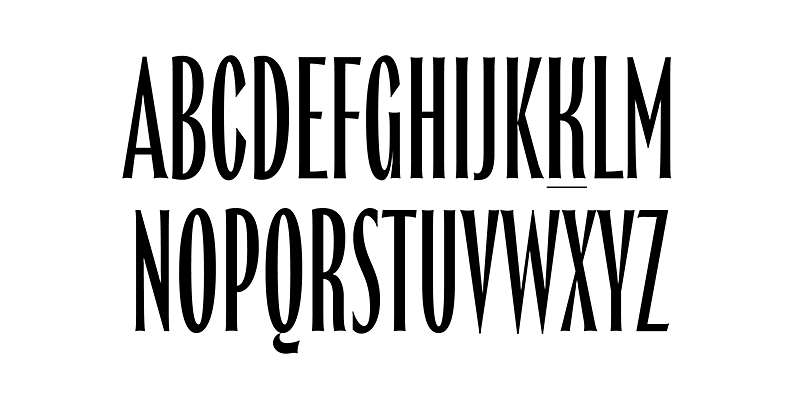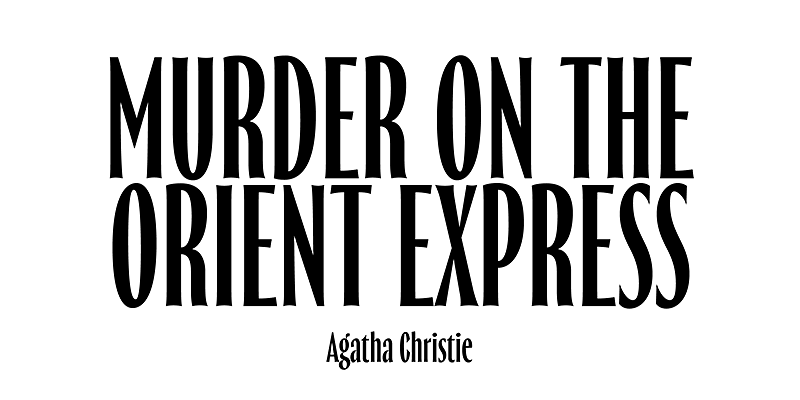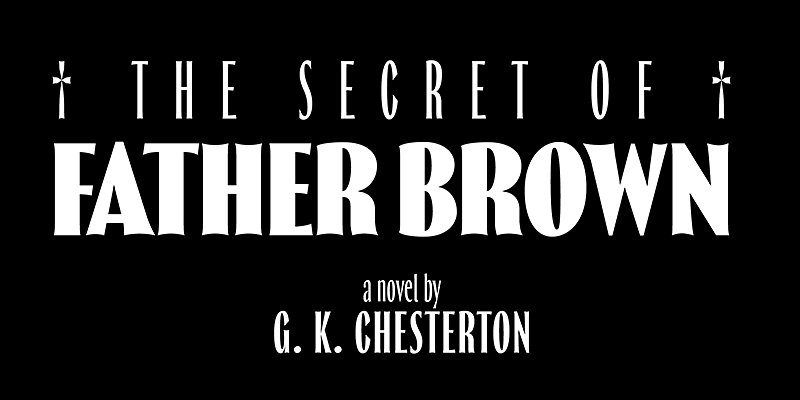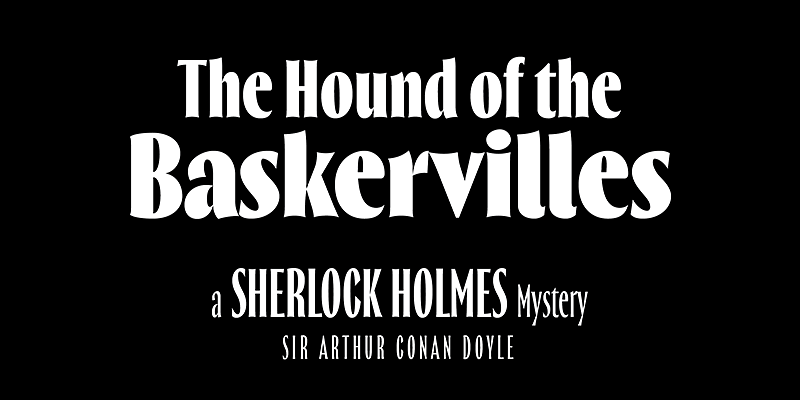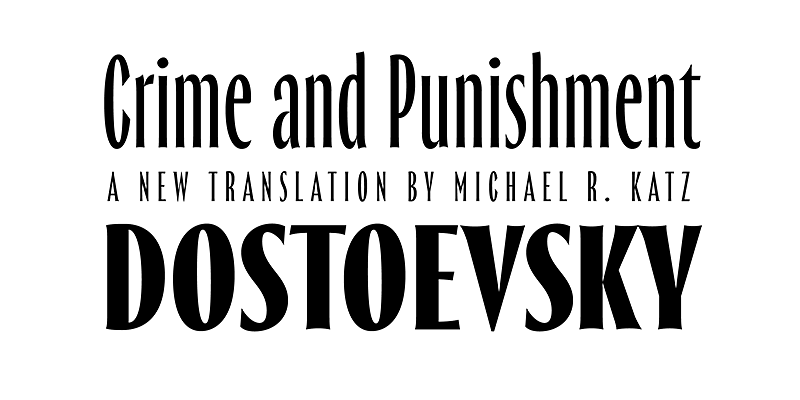
Thrillers ist eine Schrift, die an die visuelle Landschaft von Krimi-Titeln erinnert. Diese kontrastreiche Super Condensed Semi-Serif umfasst 6 Schnitte, die Ihnen eine Vielzahl von Optionen für Ihre Headlines, Titel und Ihr Branding bieten. Durch den minimalen Weißraum ist sie sehr prägnant und ihre ungewöhnliche Textur zieht unsere Aufmerksamkeit auf sich. Beenden Sie die Spannung und probieren Sie sie aus!